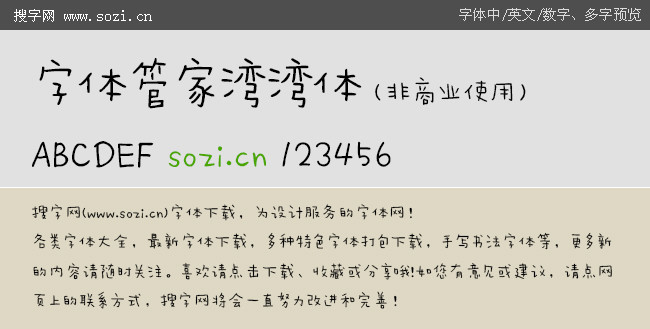
字體管家灣灣體(非商業(yè)使用)
搜字網(wǎng)給大家提供一款字體管家灣灣體(非商業(yè)使用)中文字體下載,該字體是一款個(gè)性的藝術(shù)字體,字體樣式可愛(ài),富有趣味。適合兒童包裝畫(huà)冊(cè)、書(shū)籍海報(bào)等廣告設(shè)計(jì)應(yīng)用(此字體為個(gè)人非商用版,商用可以聯(lián)系QQ:1006760504)。